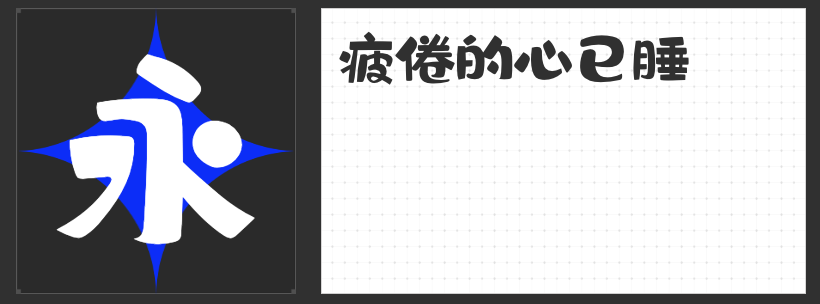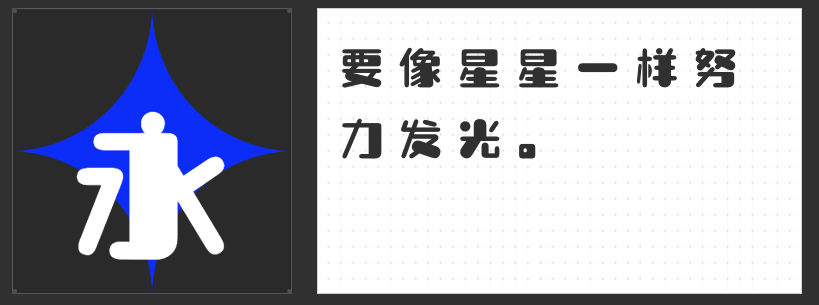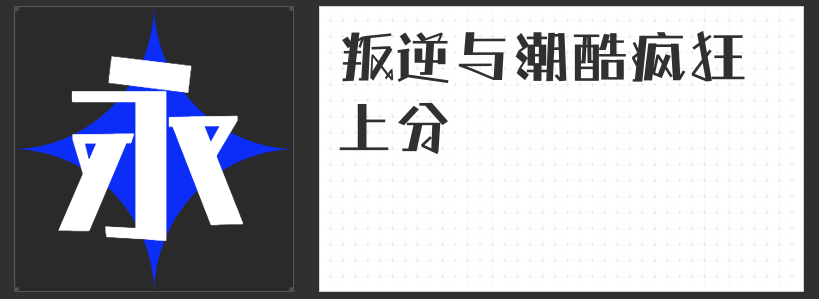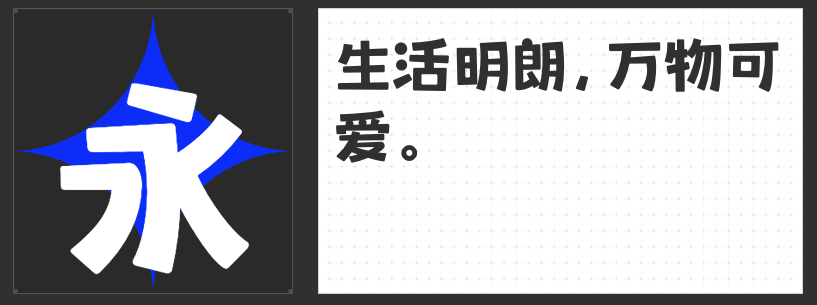
四款风格化字体推荐:解锁微信公众号设计的视觉新维度
在微信公众号的内容生态中,字体不仅是信息传递的载体,更是塑造品牌调性、强化视觉记忆的关键元素。以下四款风格鲜明的字体,以独特的设计语言与情感表达,为公众号设计注入差异化竞争力,助力内容在信息洪流中脱颖而出。
一、喵字芒果体
专为芒果农产品打造的定制字体,将热带果实的鲜活生命力凝练于笔画之间。圆润流畅的线条模拟芒果饱满的形态,微妙的弧度变化暗含阳光照射下的光影层次,仿佛能嗅到果香四溢的清新气息。这款字体适用于农业、食品类公众号,通过视觉化的自然符号传递产品的新鲜度与品质感,让文字成为连接用户与自然的情感纽带。
二、喵字动漫体
以动漫美学为核心,通过笔画间的微妙“松动感”重构传统标题字的秩序。字形的轻微倾斜与笔画末端的动态收尾,营造出漫画分镜般的叙事节奏,既保留汉字结构,又赋予其二次元文化的轻盈气质。适合游戏、动漫、青年文化类公众号,用字体构建沉浸式阅读场景,唤醒用户的共鸣与互动欲。
三、励字憨憨简
以圆弧形笔画为核心,通过夸张的笔画粗细对比与饱满的字形结构,塑造出无攻击性的可爱形象。装饰性元素如圆点、弧线的巧妙融入,让文字本身成为视觉焦点。这款字体适用于亲子、萌宠、生活方式类公众号,用温暖治愈的视觉语言传递轻松愉悦的内容氛围,增强用户情感黏性。
四、字恋狂拙黑简
以纯直线笔画与横细竖粗的强烈对比,构建出工业感与手写温度并存的矛盾美学。切口平直的笔画末端与局部连笔设计,既保留黑体的简洁力量,又融入街头涂鸦的随性态度。适合潮流、音乐、亚文化类公众号,用字体彰显年轻群体的态度表达,打造独具辨识度的视觉标识。
这四款字体通过形态、质感与文化符号的深度融合,为公众号设计提供了超越常规的视觉解决方案。选择与内容调性契合的字体,让文字从信息载体升级为情感媒介,或许正是提升用户阅读体验的隐藏密码。